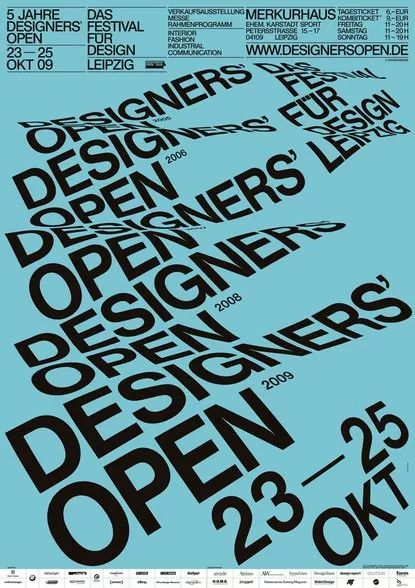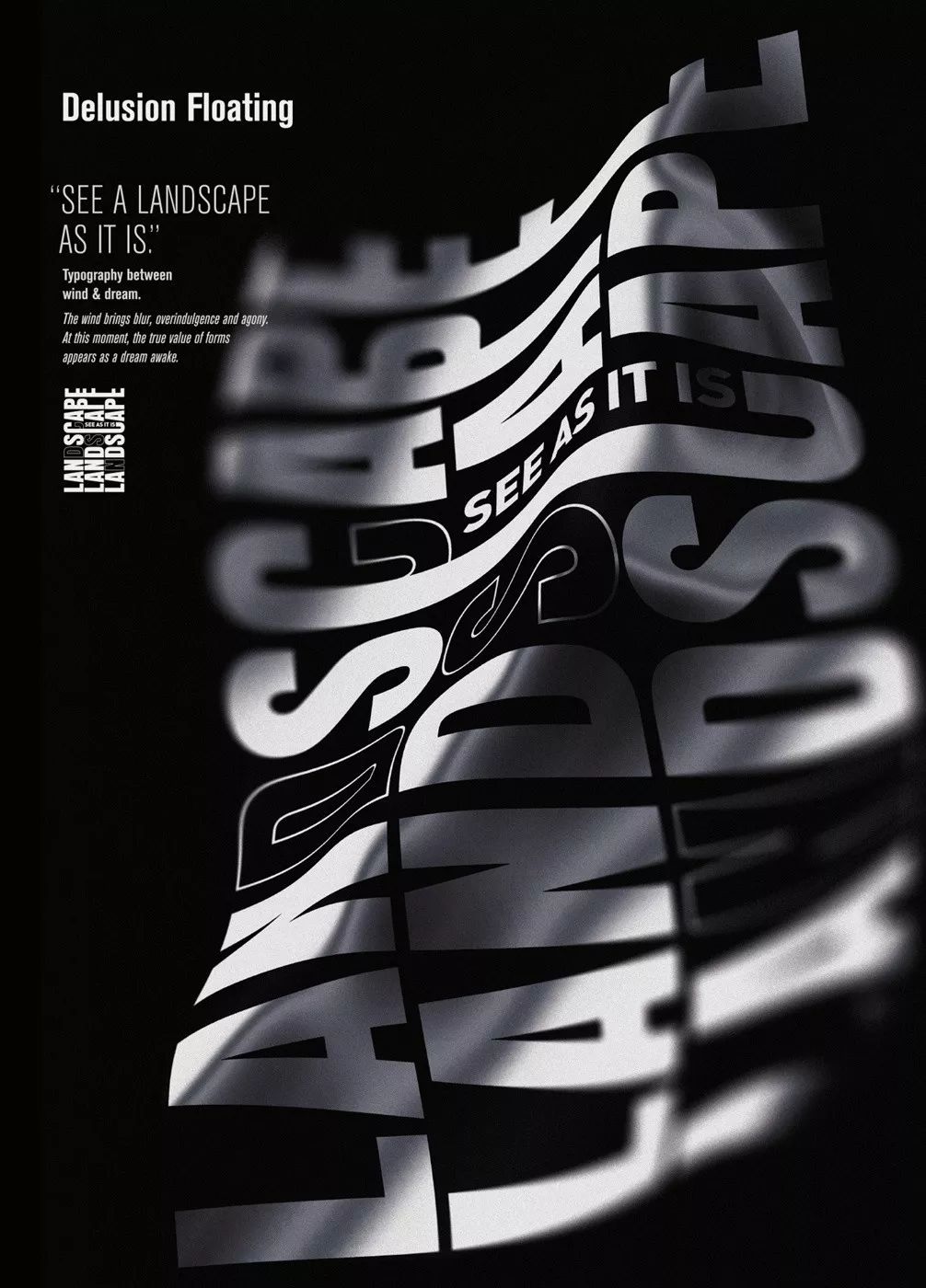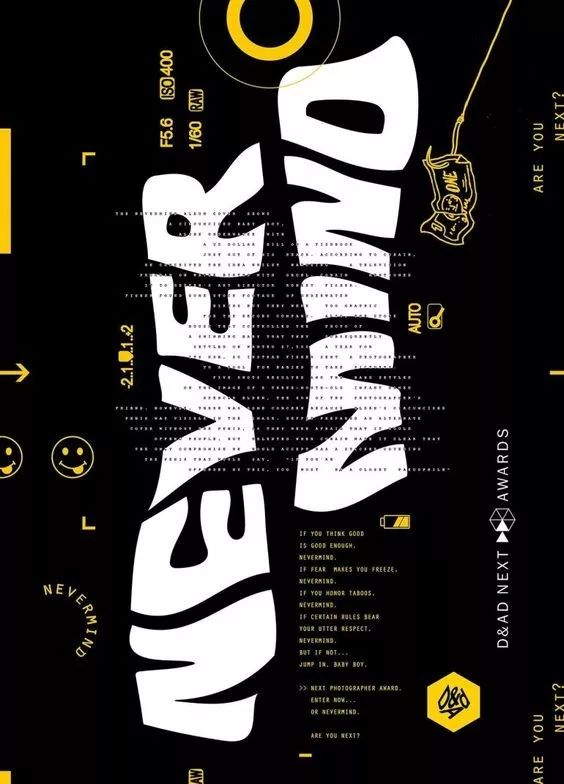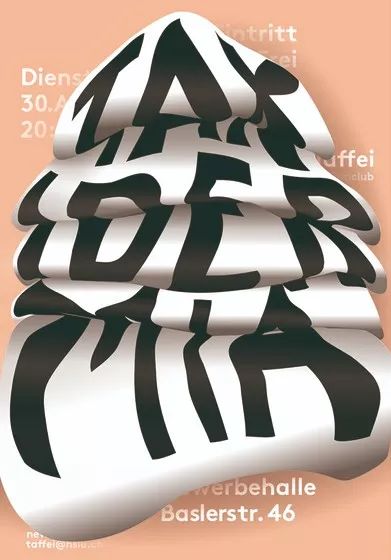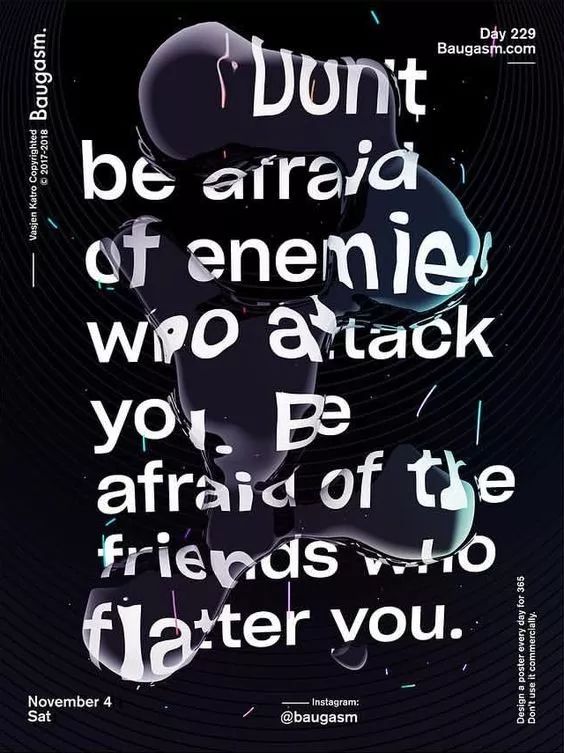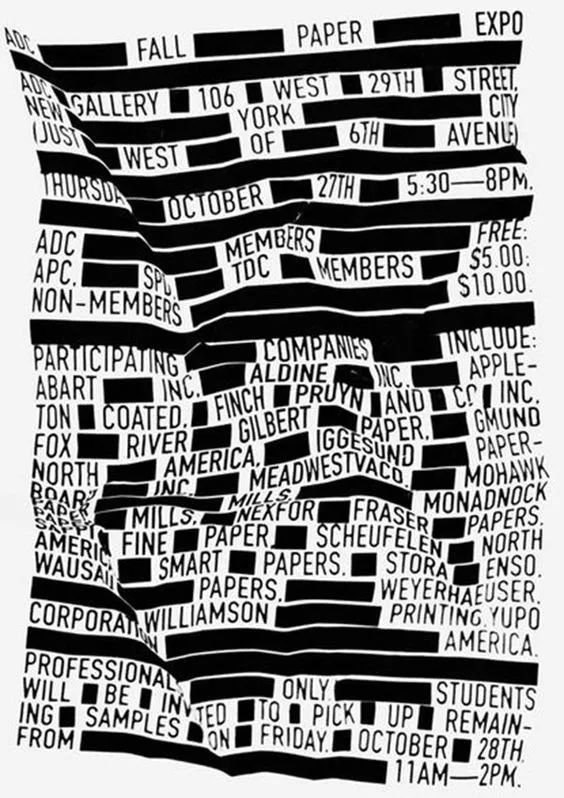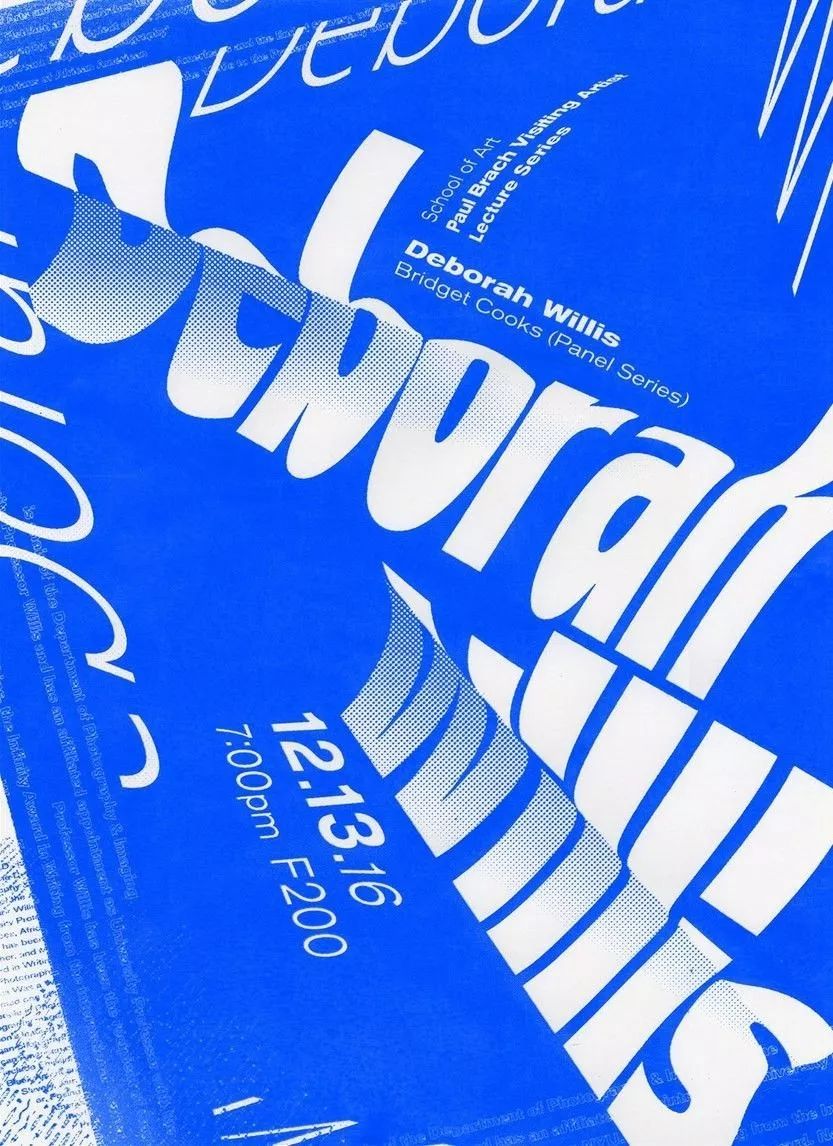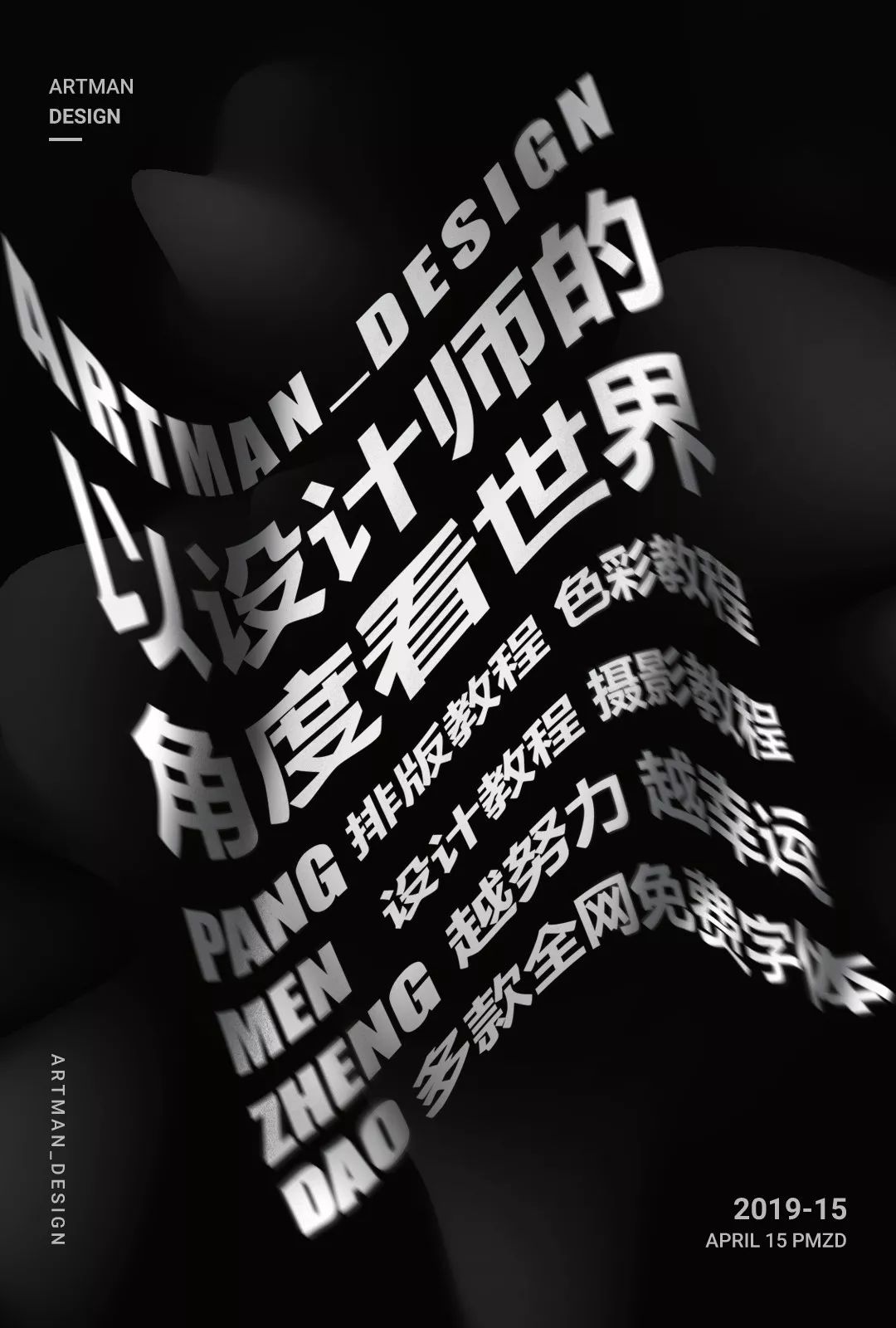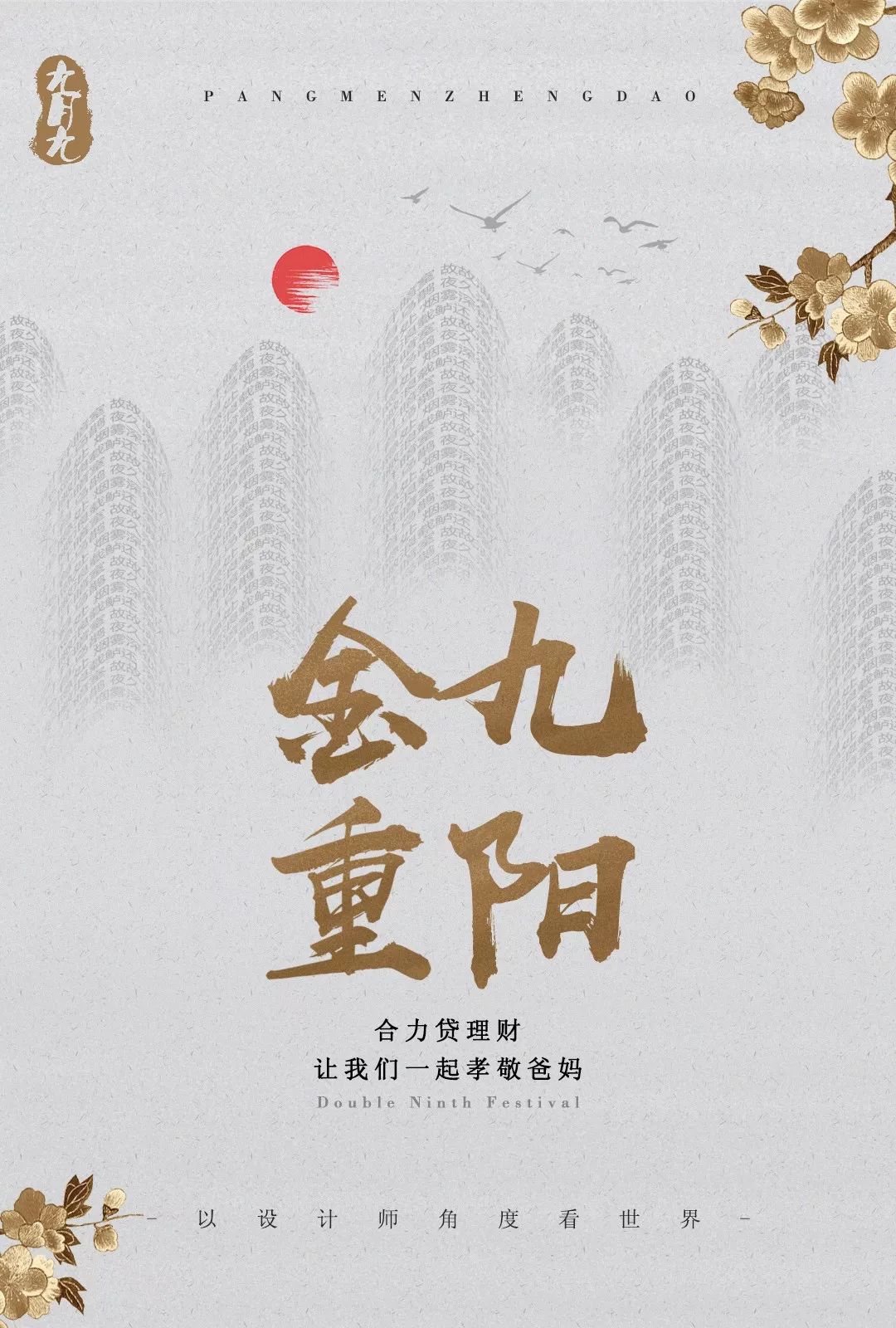
字体如何风骚扭曲?扭曲文字海报设计分享
赶紧开课,开始前先看几张海报
这些扭曲文字海报是不是羡慕坏了?
是不是非常想知道怎样做的?
是不是觉得做起来惧难?
不怕今天教你用 AI 三种方法
搞定扭曲文字效果
先用文字工具打好要用的文字,选中文字执行对象菜单下-封套扭曲-用变形建立。在弹出的变形选项对话框里进行参数更改,先勾选中预览,样式:扭转,弯曲水平垂直的数值都可以随意更改确定即可。
回到画布中还可以用小白箭头选中文字里扭曲的某一个点在任意修改扭曲角度方向等编辑,直至效果满意。
在变形选项弹出框里的样式还有很多种形状供选择,比如旗形、波形等,可以用上面的方法同样进行形状的调整。
这个方法是不是方便又精准
先打好字选中字,用钢笔工具随意勾勒个形状,同时选中文字和图形执行对象菜单下-封套扭曲-用顶层对象建立。文字马上以刚画图形形状展示了,用白箭头做微小调节完工。
就是这么简单
选中打好文字执行对象菜单下-封套扭曲-用网格建立。在弹出的封套网格对话框里先勾选中预览,接着可以调整网格行数和列数确定。这时用小白箭头对字进行角度调整即可。
以为上三个方法还有一个共同点,就是完成封套扭曲后,想再次调整扭曲效果可以点击工具栏里的网格工具对扭曲进行再次编辑。当网格工具鼠标靠近扭曲边框时鼠标出现小加号就可以增加一行或一列,按住ALT鼠标变成减号可以减少一行或一列,也可选中一列或一张的锚点进行整体移动扭曲使文字有规律性。
来下面实际案例操作时间
马上用学到的方法做个海报来看看
来看看静态高清图
是不是很简单呀
来试下把文字扭曲成图形做海报试试
虽然只是个非常小的细节
但是背后的小字其实是
首王维的重阳节诗
《九月九日忆山东兄弟》
独在异乡为异客,每逢佳节倍思亲。
遥知兄弟登高处,遍插茱萸少一人
再来看下高清原图
这个只是个功能示范
可以做出来的设计肯定是千千万万种
你学完了记得要做一个属于自己的设计练习!